La pagina dedicata ai kinetic fonts propone una selezione di caratteri progettati per trasmettere movimento, velocità e impatto visivo. L’articolo raccoglie risorse utili per chi lavora su poster, branding, contenuti social, grafiche sportive e progetti digitali in cui il testo non deve soltanto essere letto, ma anche percepito come un elemento dinamico.
Una raccolta di font kinetic pensata per progetti ad alta energia
La selezione si distingue perché non si limita a presentare font esteticamente moderni, ma mette insieme soluzioni tipografiche che evocano ritmo, potenza e direzione. Il valore principale della raccolta sta proprio nella varietà, perché accanto a caratteri più tecnici e futuristici compaiono proposte più fluide, versatili e adatte a contesti creativi differenti.
I font più adatti a comunicare velocità, sport e tecnologia
Tra le risorse più interessanti emergono font come Speed Fez, Track Drift, Speed, HIGH SPEED, NOS e Neospeed, tutti costruiti attorno a un immaginario visivo fatto di corse, accelerazione e scenari futuristici. Questi caratteri funzionano particolarmente bene quando il progetto deve suggerire potenza e performance, ad esempio per loghi automotive, eventi sportivi, esports, packaging energici o campagne promozionali dal tono aggressivo.
Accanto a queste soluzioni, l’articolo propone anche famiglie più duttili come Energize, Motion, Tracker e Beast, che permettono di mantenere un forte senso di dinamismo senza rinunciare alla leggibilità. La loro utilità cresce nei progetti che richiedono equilibrio tra personalità e chiarezza, soprattutto quando il font deve adattarsi a titoli, sottotitoli, materiali digitali e applicazioni di brand identity.
Le proposte più efficaci per branding, poster e contenuti digitali
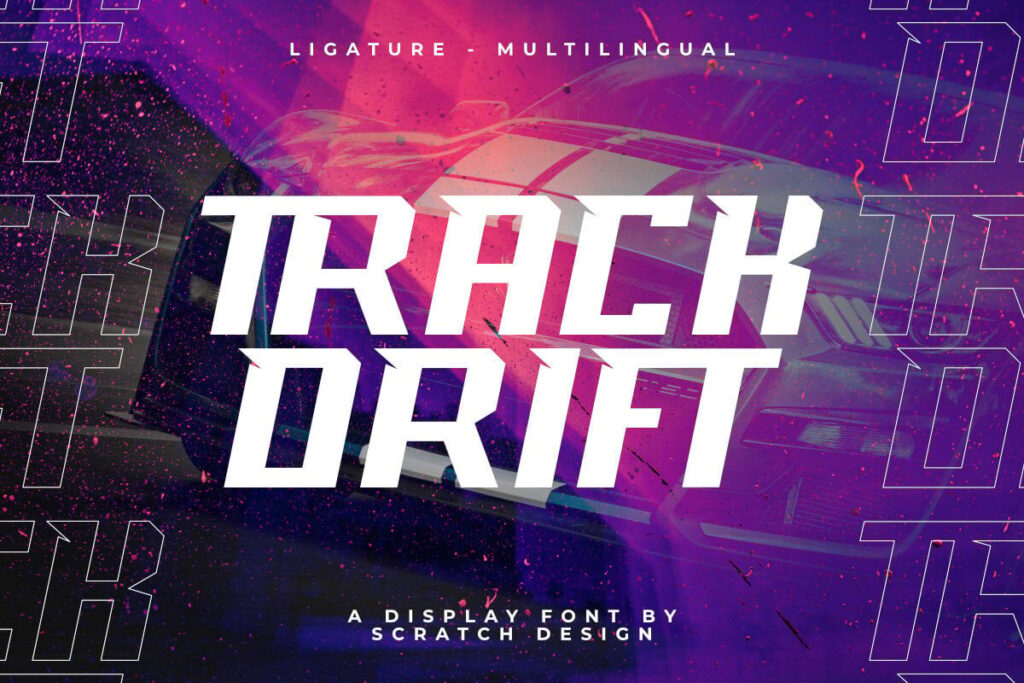
Una parte importante della raccolta è composta da font pensati per costruire titoli che catturano l’attenzione con immediatezza, come Wush, Racing Crime, Throttle, FastSpeed, Crows Driven, Fast Racer e Chaser. In questi casi la forma delle lettere diventa parte del messaggio, perché linee taglienti, inclinazioni decise e geometrie marcate aiutano a costruire un’identità visiva memorabile anche con poche parole.
Queste risorse risultano particolarmente adatte a chi deve realizzare copertine, banner pubblicitari, locandine per eventi, grafiche per videogiochi o contenuti destinati ai social network. L’articolo mostra con chiarezza come il kinetic font non sia solo una scelta estetica, ma uno strumento per aumentare la tensione visiva e dare più carattere al messaggio.
Le alternative gratuite da tenere in considerazione
La raccolta non trascura chi cerca soluzioni accessibili e include anche alcuni font gratuiti come Sprintura, Gutsand, Speedtrap e Siegra. Si tratta di risorse interessanti per test creativi, bozze, progetti personali o concept iniziali, perché consentono di sperimentare un’estetica energica e contemporanea senza partire subito da un acquisto.
Questa parte dell’articolo è utile soprattutto per designer freelance, studenti e creativi che desiderano ampliare rapidamente il proprio arsenale tipografico. La presenza di opzioni free rende la raccolta più pratica e inclusiva, permettendo di valutare diversi stili prima di scegliere una soluzione più specifica o professionale.
I consigli tipografici che rendono davvero efficace un kinetic font
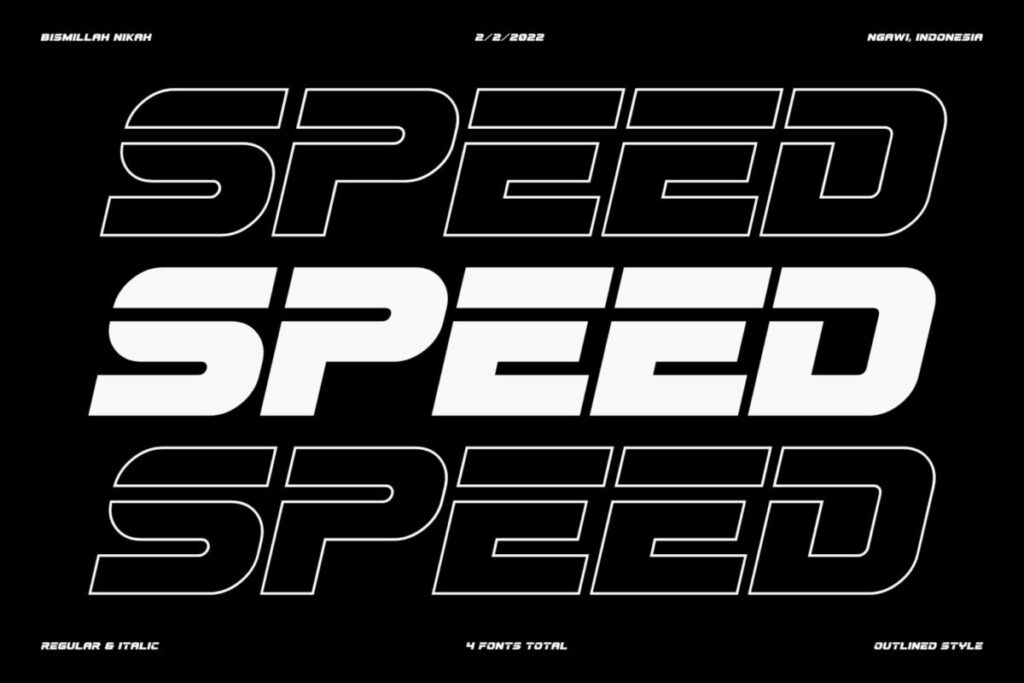
Oltre alla selezione di caratteri, la pagina offre anche una serie di suggerimenti utili per usare al meglio questo stile tipografico. Viene messo in evidenza che la scelta del font deve partire da basi solide, privilegiando caratteri con una personalità forte ma sufficientemente leggibili, perché l’energia visiva non deve mai compromettere la comprensione del testo.
L’articolo insiste anche sull’importanza di ritmo, scala, prospettiva, coerenza del movimento e adattamento ai diversi dispositivi. Questo approccio rende la raccolta più di una semplice vetrina di font, trasformandola in una guida concreta per progettare titoli e composizioni che risultino dinamiche, leggibili e coerenti con il messaggio.
Un percorso utile per chi cerca ispirazione tipografica contemporanea
Nel complesso, la pagina rappresenta una risorsa ben costruita per chi vuole esplorare il mondo dei kinetic fonts con un taglio pratico e visivamente orientato. La combinazione tra font premium, opzioni gratuite e suggerimenti d’uso permette di individuare più facilmente la soluzione giusta in base al tono del progetto, al supporto di destinazione e al pubblico finale.
La raccolta si rivela particolarmente preziosa per chi lavora in ambiti dove il testo deve trasmettere azione, modernità e presenza scenica.